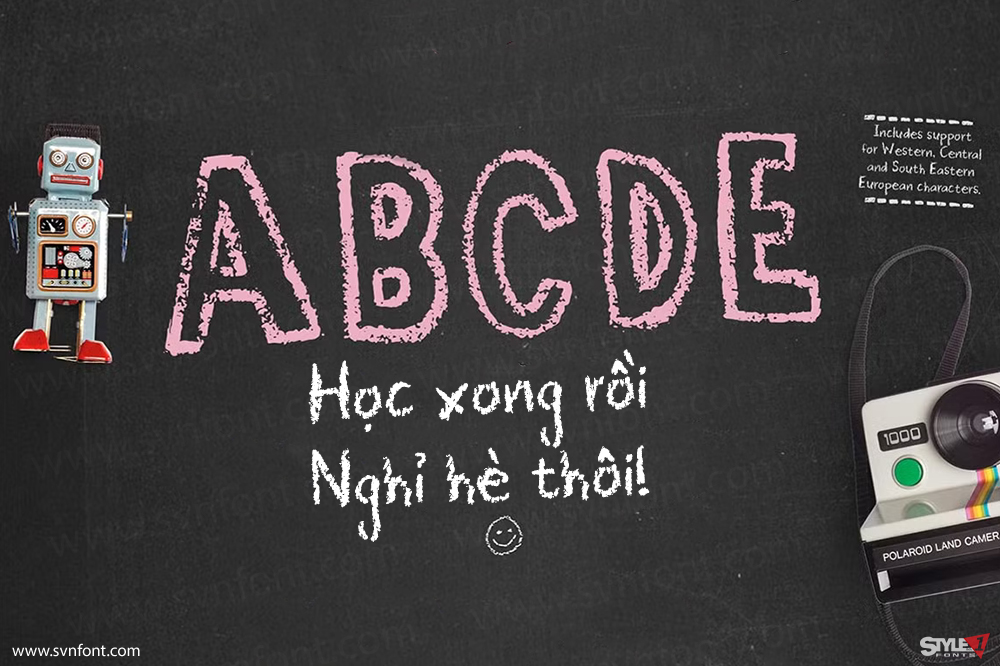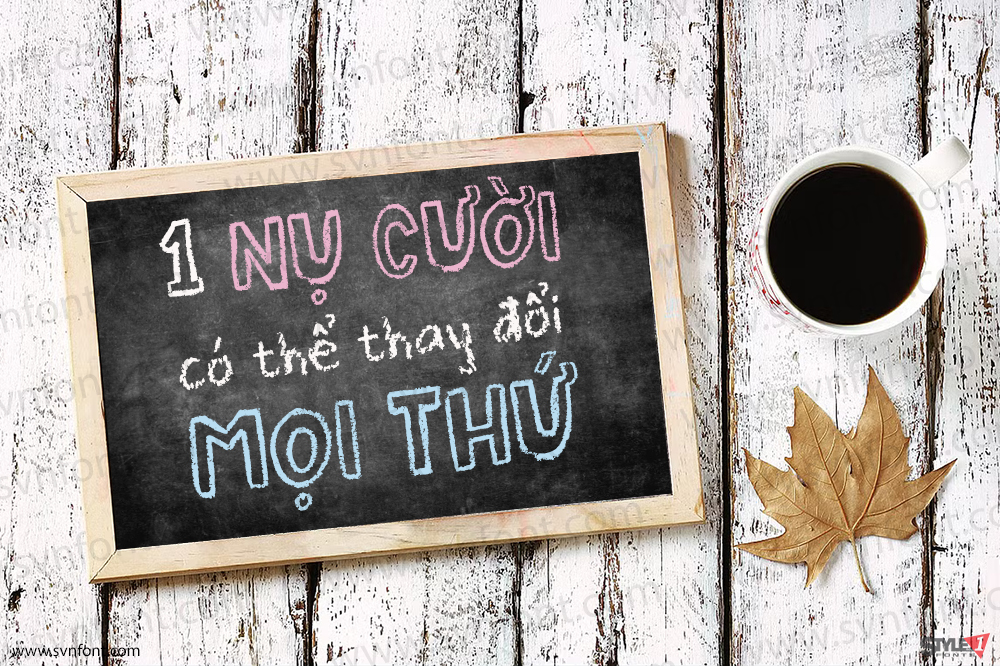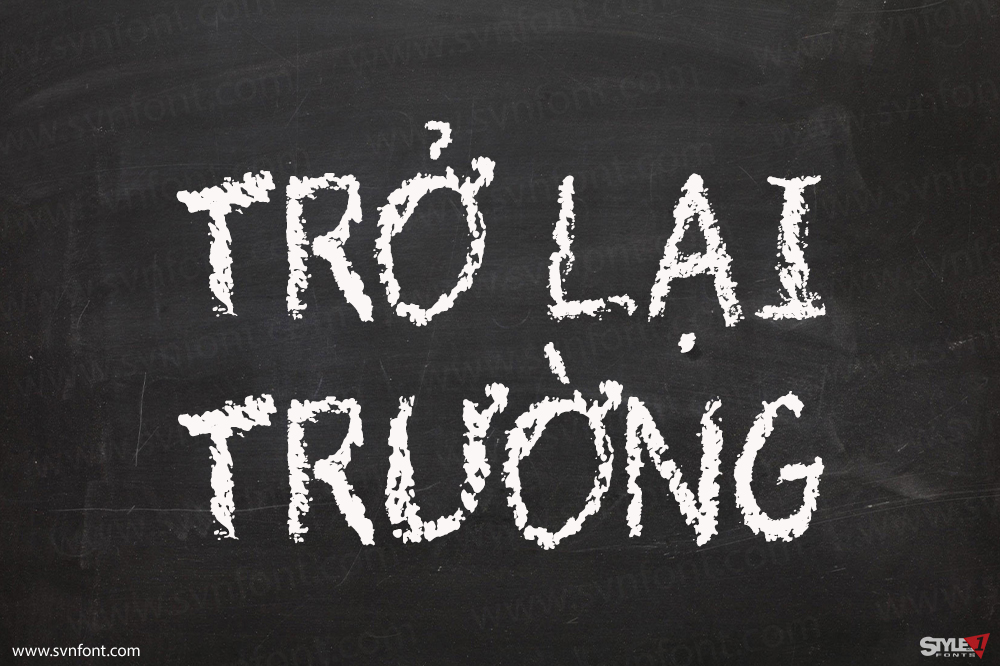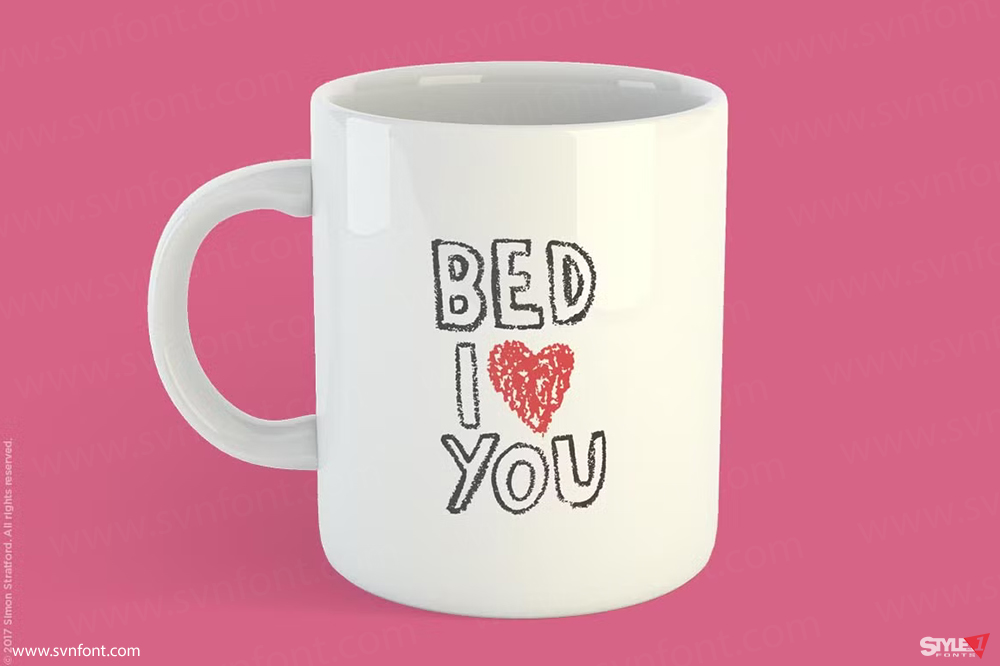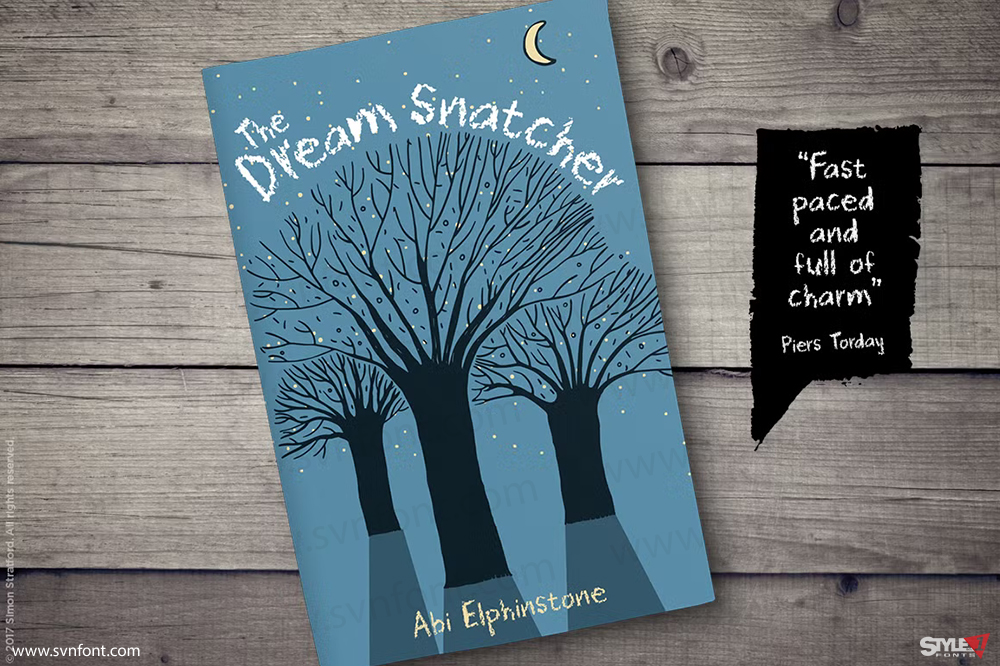
Tuck shop được tạo ra thủ công bằng phấn thật và bảng đen đá phiến tự nhiên. Nó có vô số chi tiết và kết cấu tinh tế mà bạn không thấy ở các phông chữ phấn khác. Đây là một phông chữ phấn hiển thị mang đậm nét trẻ con, ngây thơ. Bởi vì nó được vẽ tay bằng phấn thật, nên nó thô ráp, không gọn gàng và có vẻ lộn xộn, nhưng điều đó lại làm tăng thêm vẻ quyến rũ như phác thảo vui nhộn của nó.
Nó gợi nhớ cho tôi về trường học và những tấm bảng đen bên ngoài các quán cà phê, nhà hàng, quán bar và quán rượu. Đây là một phông chữ hoàn hảo để có được vẻ ngoài của một biển hiệu cửa hàng viết tay cổ điển. Kiểu phấn viền cũng sẽ lý tưởng cho sách thiếu nhi, sổ Bullet Journal, bao bì và áp phích vì nó mang tính vui nhộn và thoải mái. Nó sẽ tuyệt vời cho bất kỳ dự án nào đòi hỏi giao diện và cảm giác của phấn hoặc bảng đen.
Tóm lại, phông chữ bảng đen Tuck shop có ba kiểu: Regular (thường), Outline (viền) và Decoration (trang trí). Kiểu Decoration là một tập hợp các họa tiết trang trí, tổng cộng 77 họa tiết. Bao gồm mọi thứ từ ngôi sao và bong bóng thoại đến mũi tên và đường gạch chân đứt nét — tôi chắc chắn nó sẽ có thứ gì đó tiện dụng cho bạn sử dụng.